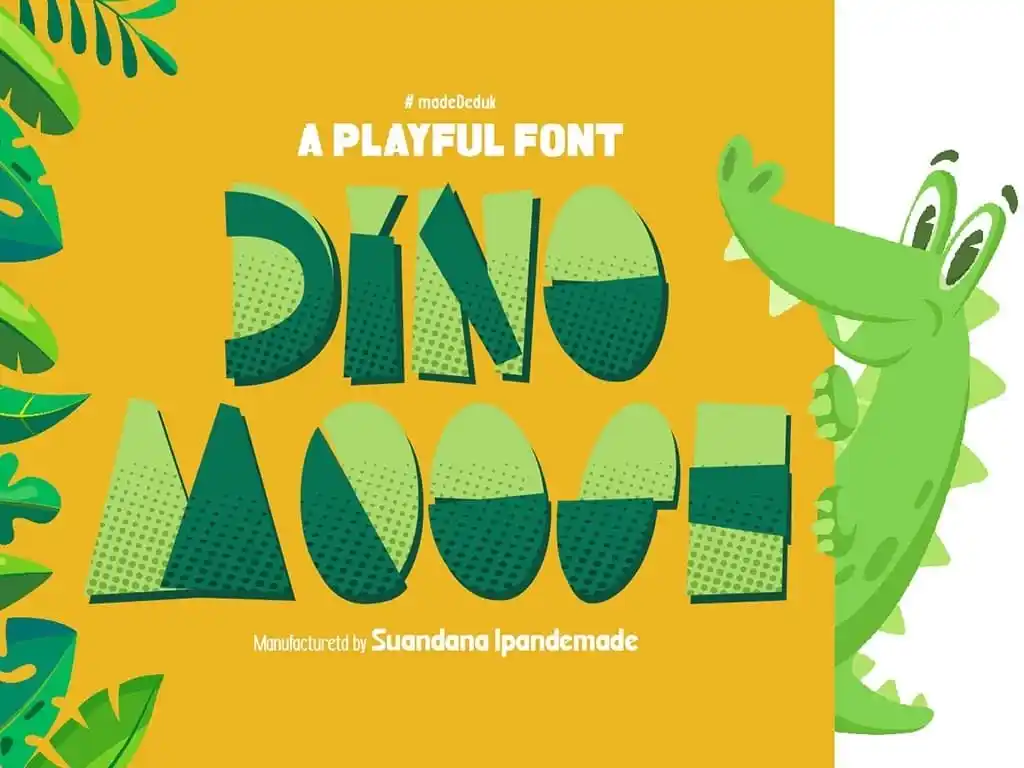
Dino Moose Font – Download Grátis
A Dino Moose Font é uma seleção divertida e vibrante que se destaca na categoria de fonts display, perfeitamente adaptada para uso em vários formatos. Seja ela um logo elegante ou a ilustração de um convite colorido, esta font irá dar vida ao seu design. A madeDeduk criou algo autêntico e original que você certamente vai adorar incorporar em suas camisetas, rótulos, cartazes ou mesmo como capa para livros. Esse é um dos motivos por trás de sua popularidade entre designers, produtores de branding e até mesmo artistas visuais. Seja qual for o seu objetivo designográfico, a Dino Moose Font certamente pode transformar sua criação em algo realmente especial e vibrante.